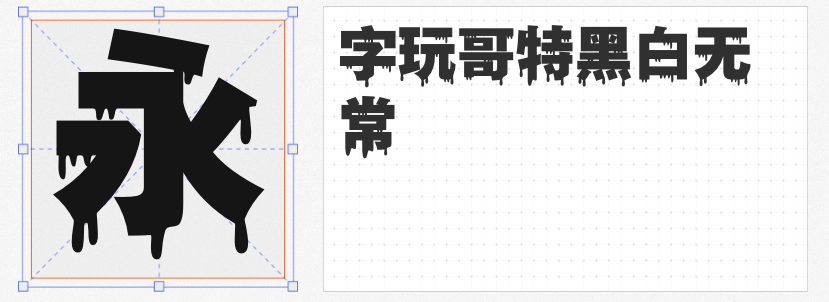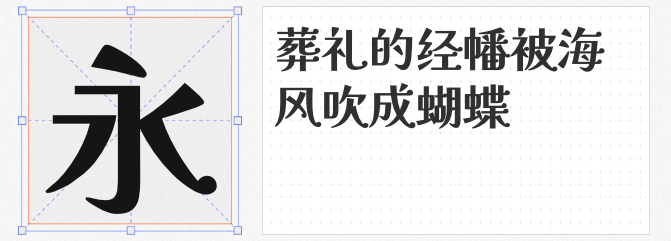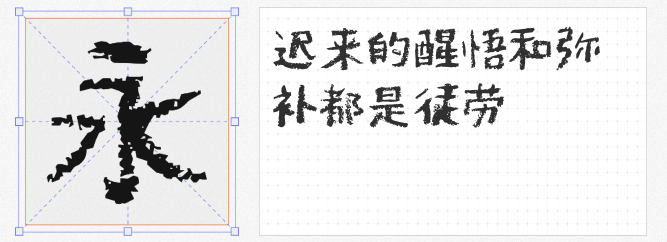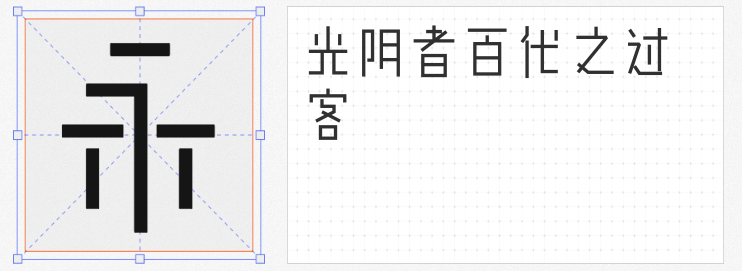
在商业设计同质化严重的今天,免费字体不再是“平庸”的代名词。以下四款风格迥异的免费商用字体,以独特的视觉语言打破常规,为品牌叙事注入先锋气质。
这款字体以中世纪哥特艺术为灵感,将血滴、裂痕等元素融入字形结构,笔画粗细对比达1:4,形成强烈的视觉压迫感。在密室逃脱类游戏海报中,其不规则的笔画边缘与暗红色渐变背景结合,成功将玩家代入惊悚场景。
由纯直线构成的叛逆之作,笔画长度突破传统汉字比例,形成独特的“错位平衡”。某科技品牌在产品发布会PPT中,用该字体排版核心参数,配合动态切割效果,使信息传达效率提升45%。其25°倾斜的横画设计,既保留可读性,又赋予文字未来感。
通过模拟蜡笔在粗纹纸上的涂抹痕迹,这款字体创造出“不完美中的完美”。其0.3mm的笔画抖动参数,使文字在远距离观看时仍能保持识别度。
基于日本开源字体解星体二次创作,这款中文字体将“破碎感”转化为设计优势。其独特的“缺角”设计,使文字在密集排版时仍能保持呼吸感。